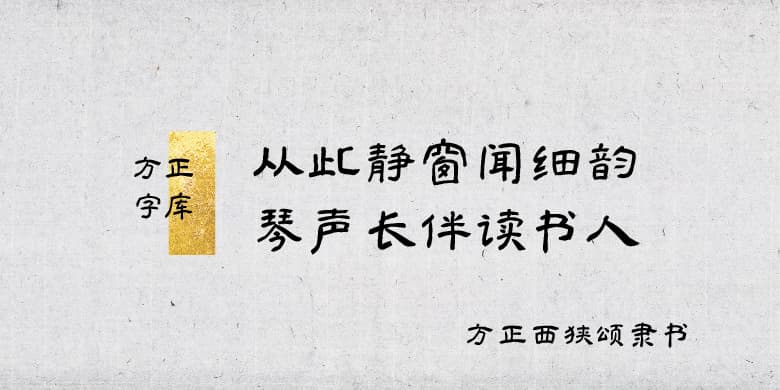
方正西狭颂隶书
品牌:方正字库中华精品字库设计师:沈学文发行时间:2021字库编码:大陆简体(GB2312-80)分类:常规书写·毛笔字体属性:精品字
关于西狭颂:
《西狭颂》(全称《汉武都太守汉阳阿阳李翕西狭颂》)。位于甘肃省成县天井山鱼窍峡。与陕西省汉中市的《石门颂》、略阳县的《郙阁颂》同列为汉代书法“三颂”,是三大颂碑中保存最完整的一座摩崖石刻。该石刻由仇靖撰文并书丹,于东汉建宁四年(171年)六月建成。有额、图、颂、题名四部分。记载武都太守李翕生平,歌颂其为民修复西狭栈道为民造福的政绩。
字体特征:
字体延续了《西狭颂》结字的格局宏阔及线条的朴茂丰腴、深厚凝重、绵长劲挺的特点。整体气势粗犷雄强而又简洁古质、结构美观而又庄严雄伟。
应用场景:
临创者:沈学文